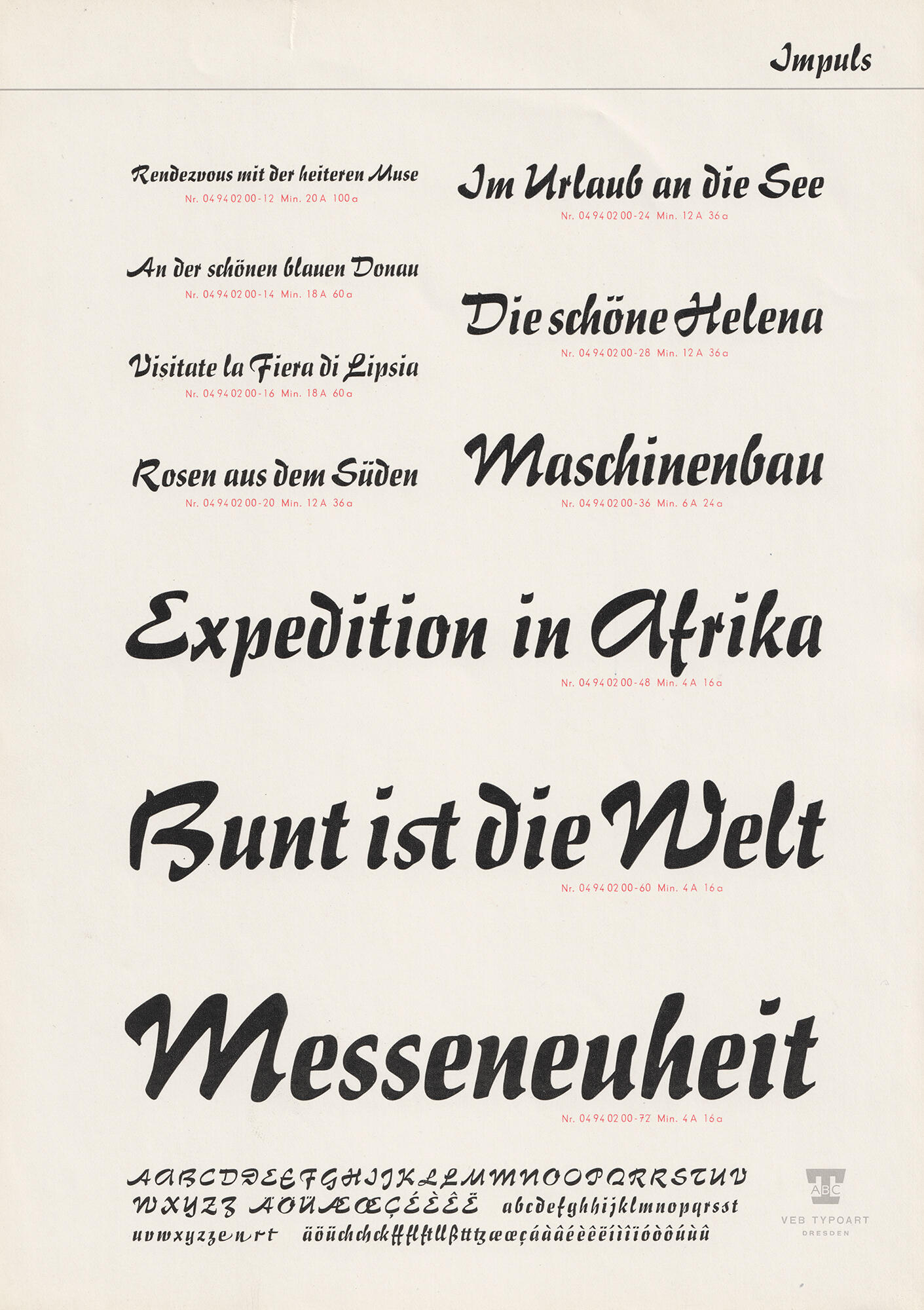
Die Impuls von Paul Zimmermann wurde ab 1954 bei Typoart als Bleisatzschrift von 12 bis 72 Punkt angeboten. Die unverbundene Schreibschrift verfügte über Varianten bei den Versalien und einige Schwungbuchstaben in den Minuskeln. Digitalisierungen gibt es von Bitstream und RMU Fonts.